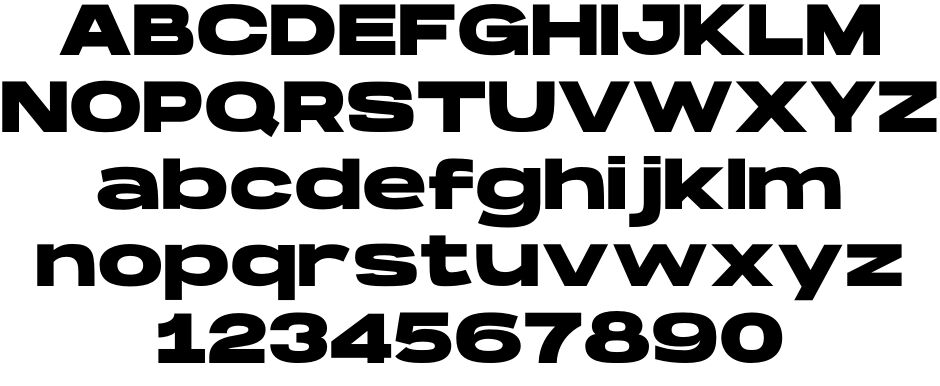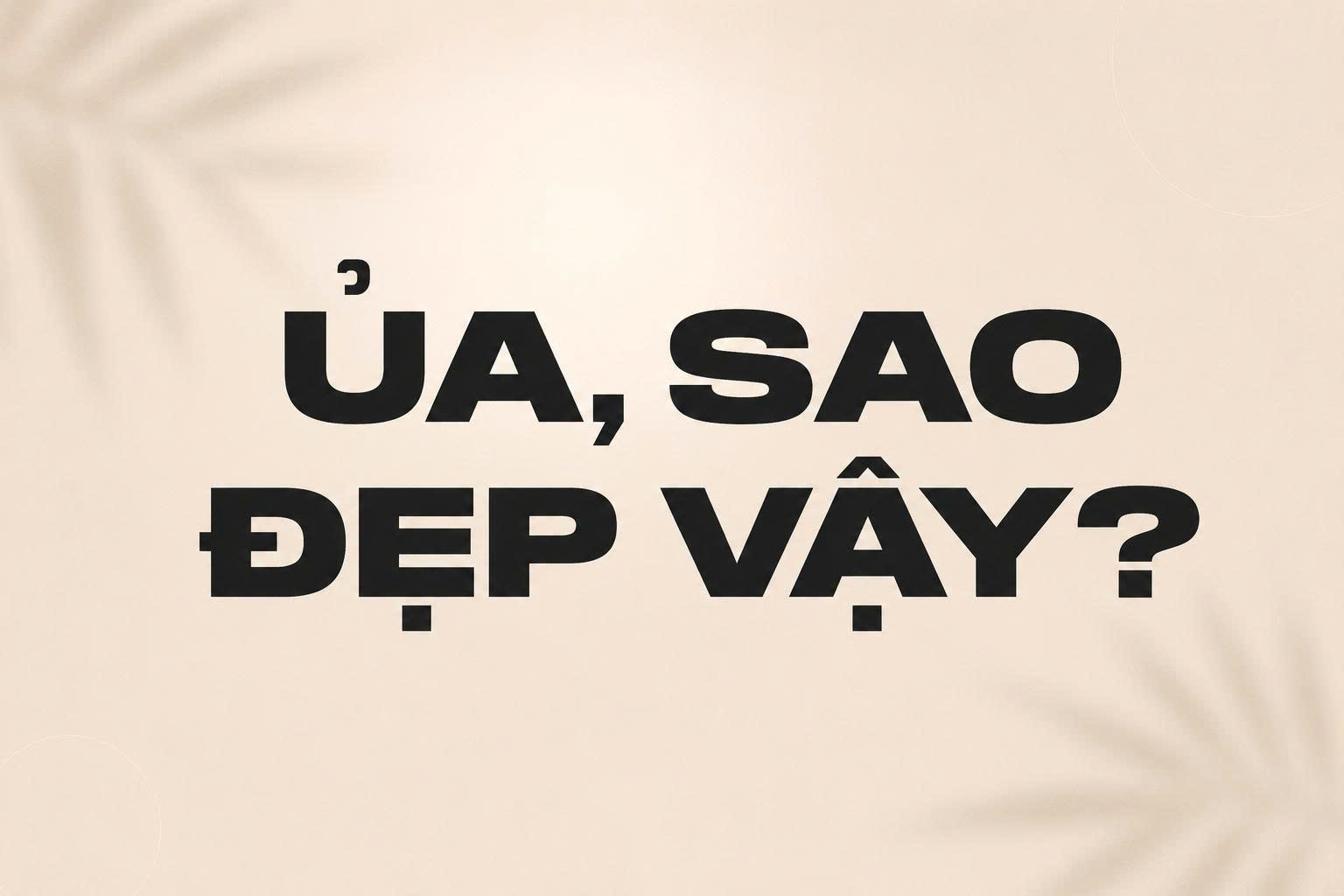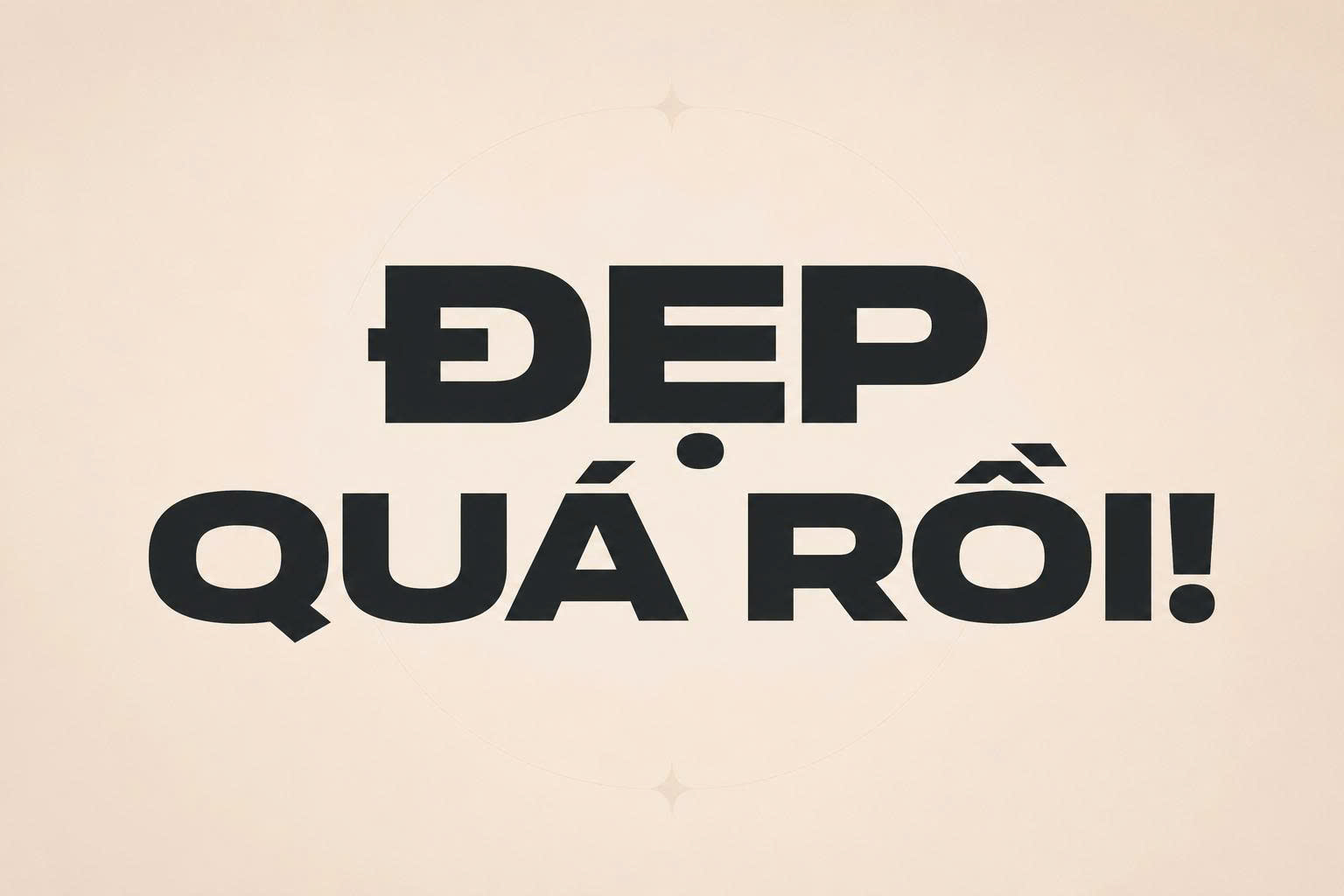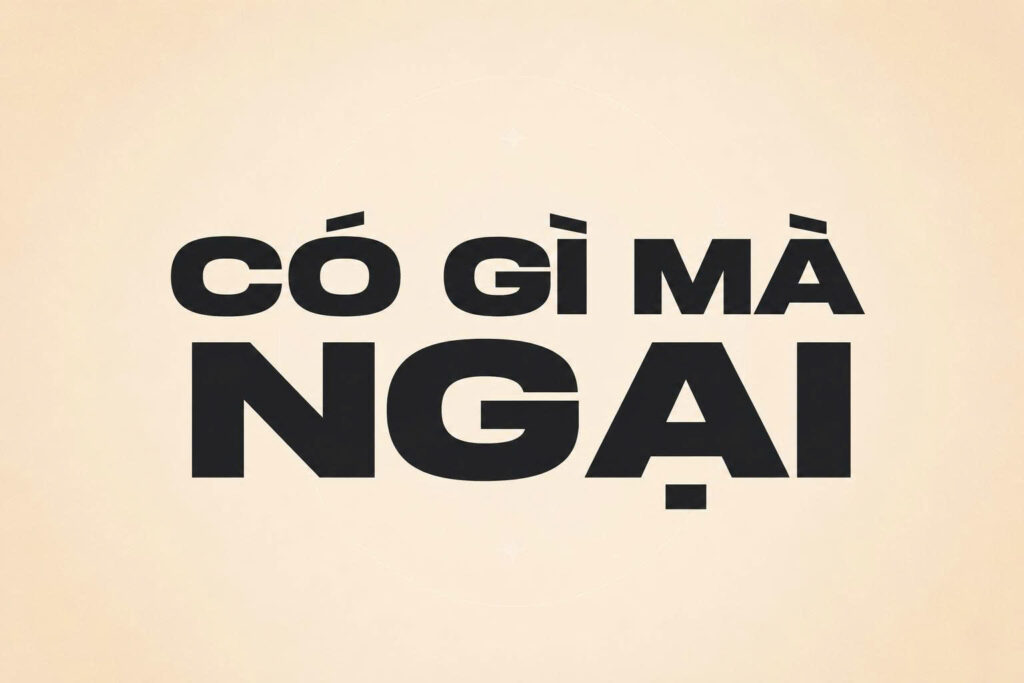
Hanson font Việt hóa là bộ phông chữ thuộc dòng Extended Ultra-bold Sans-serif mang đậm phong cách kiến trúc thô mộc và cảm hứng từ kết cấu hạ tầng công nghiệp nặng. Sở hữu các đường nét siêu dày, tỷ lệ khung chữ mở rộng tối đa theo phương ngang và các góc vát dứt khoát, DVN Hanson là chất liệu trực quan tuyệt vời để các kiến trúc sư, kỹ sư kết cấu tạo dựng sự kiên cố cho các bản vẽ phối cảnh nhà xưởng tiền chế, cổng vào khu công nghiệp container hay biển hiệu các tổ hợp giải trí thể thao mạo hiểm.
Khối chữ mở rộng bề ngang và uy lực thị giác áp đảo của Hanson font Việt hóa
Điểm cuốn hút của Hanson font Việt hóa nằm ở tỷ lệ hình học kéo giãn bề ngang (expanded) kết hợp cùng trọng lượng nét chữ đặc kín, tạo nên một bệ phóng thị giác vững chắc tựa như các khối móng bê tông đúc sẵn. Từng con chữ sở hữu các đường thẳng dập khuôn không khoan nhượng, loại bỏ hoàn toàn sự ẻo lả để hướng tới mục tiêu chiếm lĩnh không gian từ cự ly hàng trăm mét.
Sự ổn định về mặt thị giác của dòng font này giúp khẳng định tính kỷ luật, quy mô đồ sộ và uy tín của đơn vị kiến tạo công trình. Khi kết hợp cùng các bề mặt vật liệu kiến trúc hiện đại như tôn sóng container sơn màu xám chì, khung dầm thép hình chữ H, tấm kim loại đục lỗ hay mặt sàn bê tông mài thô, Hanson tạo nên sự tương thích thẩm mỹ cơ khí vô cùng mạnh mẽ.
| Phân loại phong cách | Ultra-bold Display / Extended Sans / Brutalist Industrial |
| Mục đích phù hợp | Biển tên nhà xưởng, tiêu đề bản vẽ CAD, logo công nghiệp |
Tư vấn từ chuyên viên: Hanson sở hữu độ dày nét áp đảo và bề ngang chữ rất rộng. Để bản thiết kế đạt hiệu quả thẩm mỹ tốt, bạn chỉ nên sử dụng phông chữ này cho các tiêu đề chính, mã hiệu phân xưởng hoặc tên công trình ở kích thước lớn từ 24pt trở lên.
03 Ứng dụng phông chữ Hanson vào công trình thực tế
Nhờ vẻ ngoài khỏe khoắn và tính chính xác cao, bộ phông chữ này mang lại giá trị thực tế lớn trong khâu tạo điểm nhấn cho các công trình hiện đại:
- Biển hiệu Cổng chào cho Khu Công nghiệp và Kho bãi Container: Những khối chữ mở rộng của Hanson rất ăn ý khi gia công chữ nổi bằng thép tấm hàn thô hoặc sơn stencil trên vách tôn sóng kim loại, mang lại diện mạo đanh thép và thể hiện quy mô sản xuất vững mạnh.
- Bìa hồ sơ giải pháp kết cấu thép công trình nặng: Sử dụng Hanson font Việt hóa cho tên dự án và mã hiệu tập bản vẽ giúp hồ sơ toát lên vẻ quy chuẩn, tạo niềm tin lớn với các kỹ sư thẩm tra và chủ đầu tư.
- Hệ thống biển báo cảnh báo an toàn và Cột chỉ dẫn tải trọng: Phông chữ này khi in trên các tấm kim loại sơn màu vàng cảnh báo hoặc phủ màng phản quang sẽ giúp công nhân và tài xế nhanh chóng nhận biết thông tin từ cự ly xa, tăng cường tính kỷ luật trên công trường.
03 Lưu ý bố cục Hanson font Việt hóa duy trì tính kỷ luật cơ khí
Để khai thác hiệu quả vẻ đẹp của dòng font công nghiệp nặng này mà không gây cảm giác ngột ngạt cho bản vẽ, người thiết kế nên lưu tâm một số kinh nghiệm sau:
- Nới rộng khoảng cách dòng: Do cấu trúc con chữ bè rộng theo phương ngang, bạn nên thiết lập khoảng cách dòng thoáng đãng (khoảng 1.5 – 1.6 lần cỡ chữ) để các dòng chữ không bị đè nén lên nhau, giữ được nhịp thở hiện đại cho trang in.
- Tránh sử dụng cho văn bản dài: Trọng lượng nét siêu đậm của DVN Hanson chỉ được tối ưu cho các cụm từ ngắn từ 1 đến 3 từ. Việc lạm dụng cho các đoạn văn bản giải thích chi tiết sẽ làm giảm đáng kể khả năng đọc hiểu của người xem.
- Lựa chọn gam màu công nghiệp tương phản: Hanson phát huy hiệu quả thị giác cao khi phối cùng các tông màu mang sắc thái cơ khí như vàng cảnh báo, cam đất, đen tuyền, xám sắt thép hoặc trắng tuyền trên nền tối mờ.